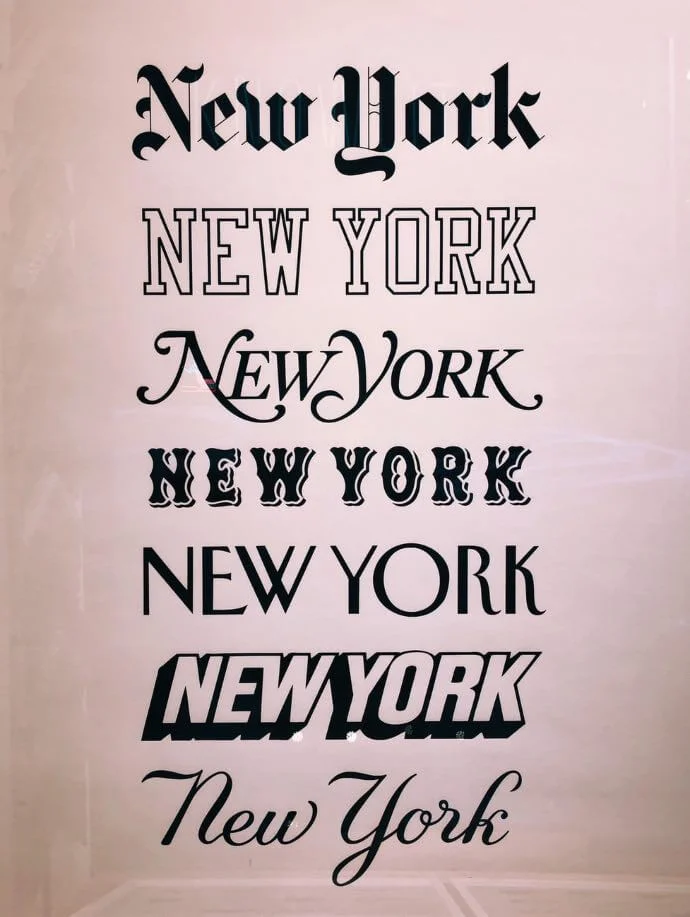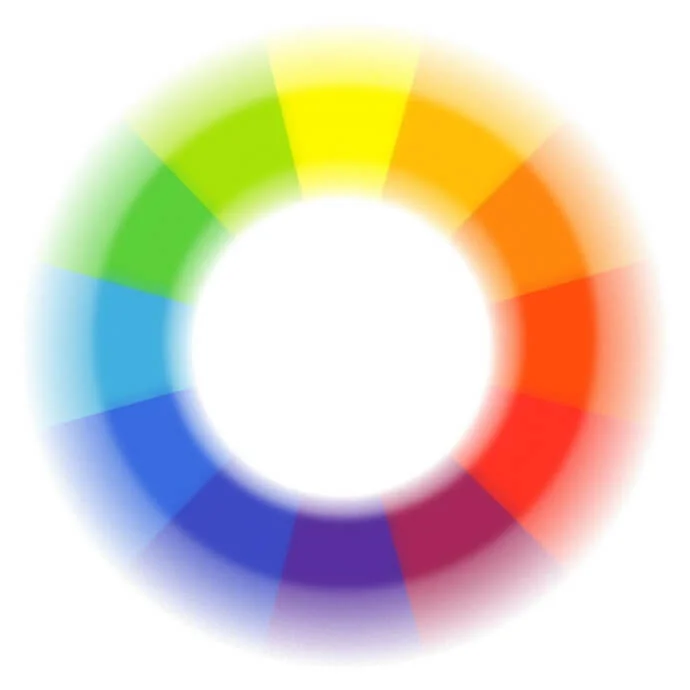
Polo donna gialla personalizzata: dritte e consigli per scegliere font e colori!
Consigli per la scelta di font e colori ideali per personalizzare una polo da donna gialla.
Le polo personalizzate economiche sono dei capi di abbigliamento molto versatili. Ideali per diverse attività sportive (come il golf e il tennis), per il lavoro e anche come capo per il giorno, tra le più richieste dalle donne troviamo quelle gialle.
Una polo da donna gialla si abbina bene a dei jeans o a dei pantaloni neri, ma anche a una gonna in jeans o bianca. In questo modo si ottiene un look casual da tutti i giorni, comodo e discretamente sportivo.
Ma come personalizzare una polo gialla? Come scegliere i colori e i font perfetti per la stampa o per il ricamo? Oggi ti forniremo preziosi consigli a riguardo, iniziando prima di tutto dai colori.
Polo donna gialla: quale colore scegliere per la stampa o il ricamo perfetti?
Quando si tratta di scegliere un colore che si abbini bene a un’altra tonalità, è necessario prima di tutto avere una comprensione di come i diversi colori funzionano (e non funzionano) insieme.
A tal proposito, la scelta vincente è quella di utilizzare la ruota dei colori.
schema colori polo gialla personalizzata
Non guardarla con sospetto: ora ti spiegheremo nei dettagli come funziona!
Colori complementari
Osserva attentamente la ruota dei colori. Qualsiasi colore situato direttamente di fronte all’altro è complementare. Ciò significa che questi colori, più le loro sfumature, tendono ad abbinarsi bene l’uno con l’altro.
Per esempio, qualsiasi tonalità di rosso si abbina bene con il verde. Arancione e blu sono una coppia perfetta.
Nel caso di una polo da donna gialla, il viola e le sue sfumature (ma anche l’indaco e il blu) sono colori perfetti per una personalizzazione con stampa o ricamo.
I colori complementari si abbinano bene tra loro per via del contrasto. Facendo risaltare sia il colore della tua polo che la scritta o il disegno, crei un equilibrio di tonalità gradevole alla vista.
Colori analoghi
Si tratta di colori che si trovano direttamente l’uno accanto all’altro sulla ruota dei colori. Per il giallo dovresti quindi scegliere il lime o le tonalità dell’oro.
I colori simili sono i più armonici tra loro, ma dovresti creare un netto contrasto per evitare che la tua scritta o il tuo disegno risultino incomprensibili.
A tal proposito potresti utilizzare dei contorni di colore più scuro in modo da evidenziare la stampa o il ricamo e renderli ben visibili!
In alternativa possiamo tralasciare la ruota dei colori e cercare una tonalità che crei comunque un netto contrasto con il giallo: nero, verde bosco e verde petrolio potrebbero essere una scelta originale.
Ora passiamo alla scelta del font. Come trovare quello perfetto?
Font perfetto su una polo da donna gialla: ecco quali caratteristiche ricercare.
font per polo personalizzate economiche
Se vuoi realizzare delle bellissime polo personalizzate economiche di colore giallo, è importante che tu scelga non solo un colore perfetto ma anche un font ideale.
Come fare? Non preoccuparti: ti aiuteremo noi! Ecco i principali fattori chiave da considerare quando cerchi un carattere tipografico appropriato:
• Identità del marchio: se si tratta di una polo gialla da utilizzare come divisa aziendale, il font dovrebbe rappresentare il carattere e lo spirito della tua azienda.
• Leggibilità: naturalmente un carattere dovrebbe essere sia chiaro che leggibile. Quando le persone impiegano troppo tempo per capire cosa c’è scritto in una frase, perdono facilmente l’interesse. Al fine di evitare questa situazione, non utilizzare caratteri troppo “fantasiosi”, perché costringono l’occhio del lettore a sforzarsi troppo. Nelle polo personalizzate, cerca di evitare i font in corsivo, come Vivaldi. Ok sono molto belli, ma sono anche molto difficili da leggere.
• Serif vs Sans. Di solito, una delle prime domande da fare quando si sceglie un carattere per il testo è: “Meglio serif o sans serif?”. Uno dei punti più importanti che ti permette di deciderlo è la lunghezza della tua frase. I caratteri serif sono, di solito, perfetti per le frasi lunghe. Ma è anche importante considerare il tuo target di riferimento.
Per stampare una polo potresti inoltre scegliere una combinazione di due font diversi. Il trucco è accostare due caratteri tipografici molto diversi (ma che si abbinano bene tra loro), in modo che ci sia un grande contrasto tra loro.
Se risultano troppo simili potrebbero semplicemente confondere il lettore.
In conclusione
Ora conosci tutti i trucchi per scegliere il colore e il font perfetto per la tua polo da donna personalizzata!